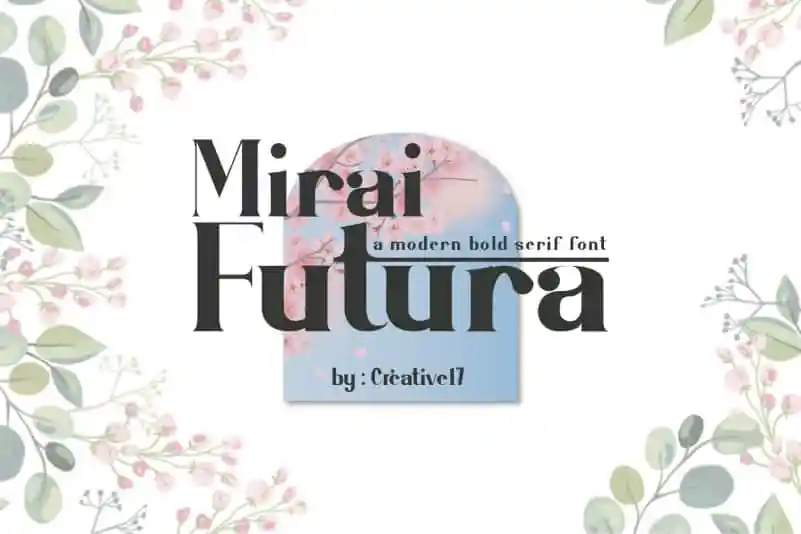
A Mirai Futura Serif é uma tipografia serif ligada moderna que incorpora elementos de contemporaneidade com um toque retro da década de 1950. Inspirada nas influências do modernismo e no estilo Art Nouveau, essa fonte traz um toque sofisticado e elegante aos projetos. É ideal para grandes trabalhos como logotipos, títulos de jornais, panfletos, cartões de visita, convites, cartas de cumprimento e outros tipos de projetos gráficos. A Mirai Futura Serif transmite um visual luxuoso e único, proporcionando uma experiência inovadora em design para seus trabalhos mais importantes. Combinada com a estética da contemporaneidade, essa fonte oferece um toque distintivo que torna seus projetos ainda mais memoráveis.